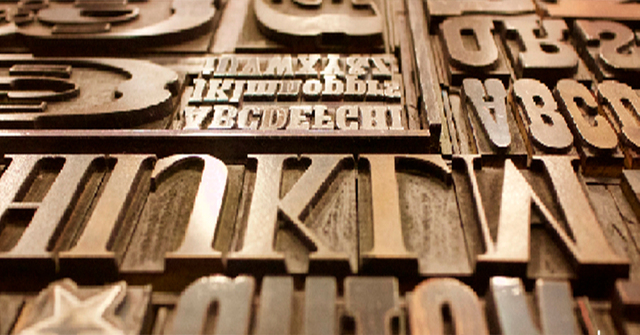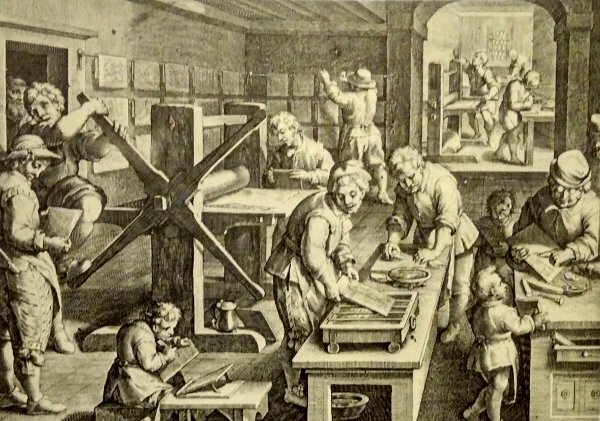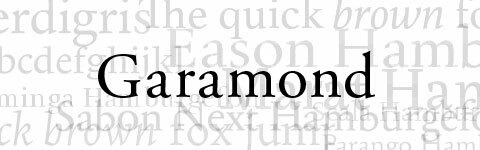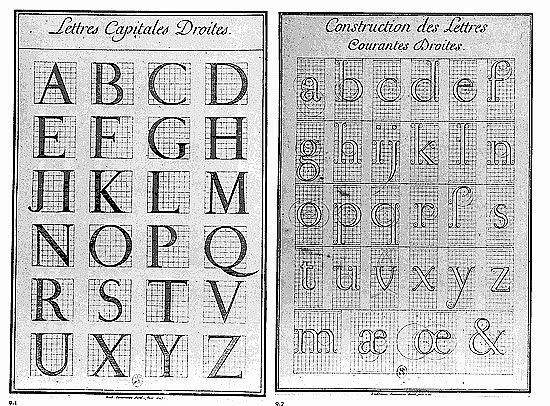
Alrededor de 1440, Johannes Gutenberg desarrolló en Alemania una técnica para elaborar unos modelos o moldes de tipo que se utilizaron para la impresión de las letras individuales.
Tal fue su éxito que se propagó el arte de imprimir en toda Europa y la técnica se perfeccionó en varios países, especialmente en Italia, donde establecieron la primera gran imprenta de ese tiempo.
Publicó el primer catálogo de tipos que se haya producido (con fuentes romanas, griegas y capitales ornamentadas)
Llegando al sigo XVI, inicia lo que es conocida como la época de oro de la tipografía francesa, destacando el trabajo de Henri y Robert Estienne, y además principalmente Simon de Colines, quien grabó varios tipos romanos, itálicos, versalitas, griegos y latinos.
Estos dos fueron personajes importantes de la época, donde Garamond contribuyó con el tipo de letra que lleva su nombre, tiene buena legibilidad y elegancia
Tanto fue la importancia de la tipografía que en 1692 el rey Luis XIV ordenó que crearan un comité de eruditos para la creación de un tipo diseñado con fines científicos. Y ese resultado fue el tipo Jaugeon, con letras en eje vertical y serifas simétricamente horizontales
Él inició la estandarización del tamaño de los tipos al publicar su PRIMERA TABAL DE PROPORCIONES y su primer libro de modelos, en 1737
La mejor prueba de la trascendencia de la tipografía fue cuando Theodore Low De Vinne mandó a realizar a finales del siglo XIX, un diseño especial para la impresión de la revista Century, fue el primer tipo especializado para una publicación
Con el crecimiento de la televisión y los avances en la tecnología tipográfica favorecieron una reinvención de la naturaleza de la tipografía; además, los cambios científicos, políticos y sociales se los años sesenta tuvieron un gran efecto inmediato.
Fue en la aparición de las computadoras y sistemas informáticos los que cambiaron todo para siempre ya que la venta del Apple Macintosh en 1982 fue el primer sistema operativo que mostraba diferentes tipos de letra que se podían elegir y aplicar en las hojas de texto, siendo esto una total revolución.